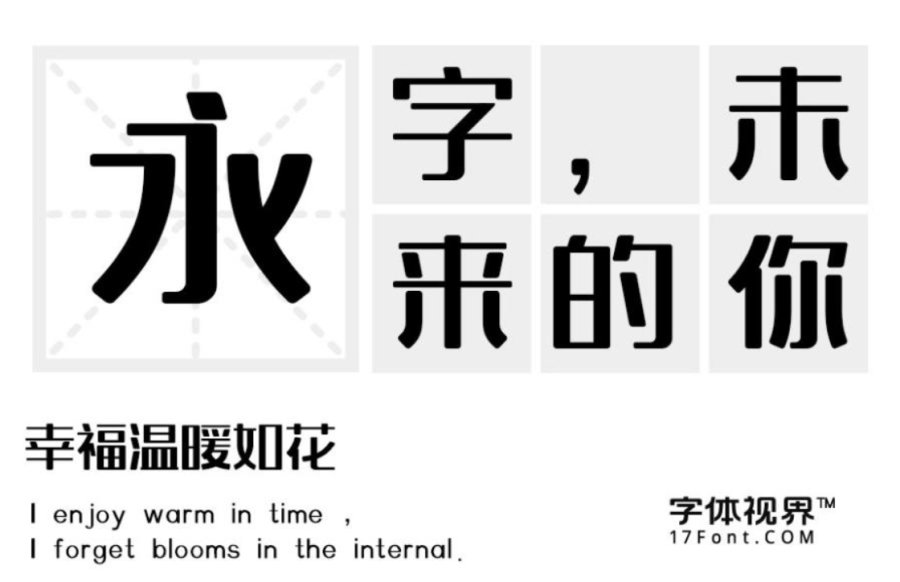
上首叮当体发布
字体名称:上首叮当体
字体类别: 创意黑体
适用场景:标题、正文、印刷、屏显、动漫、影视、广告
上首叮当体简介:上首叮当体,字体风格方正,字体笔画竖勾、竖折都做了简化的处理。字库整体特征坚硬、有力,具有现代、国际化的指向性,适用于搭配标志、广告标语、商业广告等高端属性。
上首叮当体预览图展示: